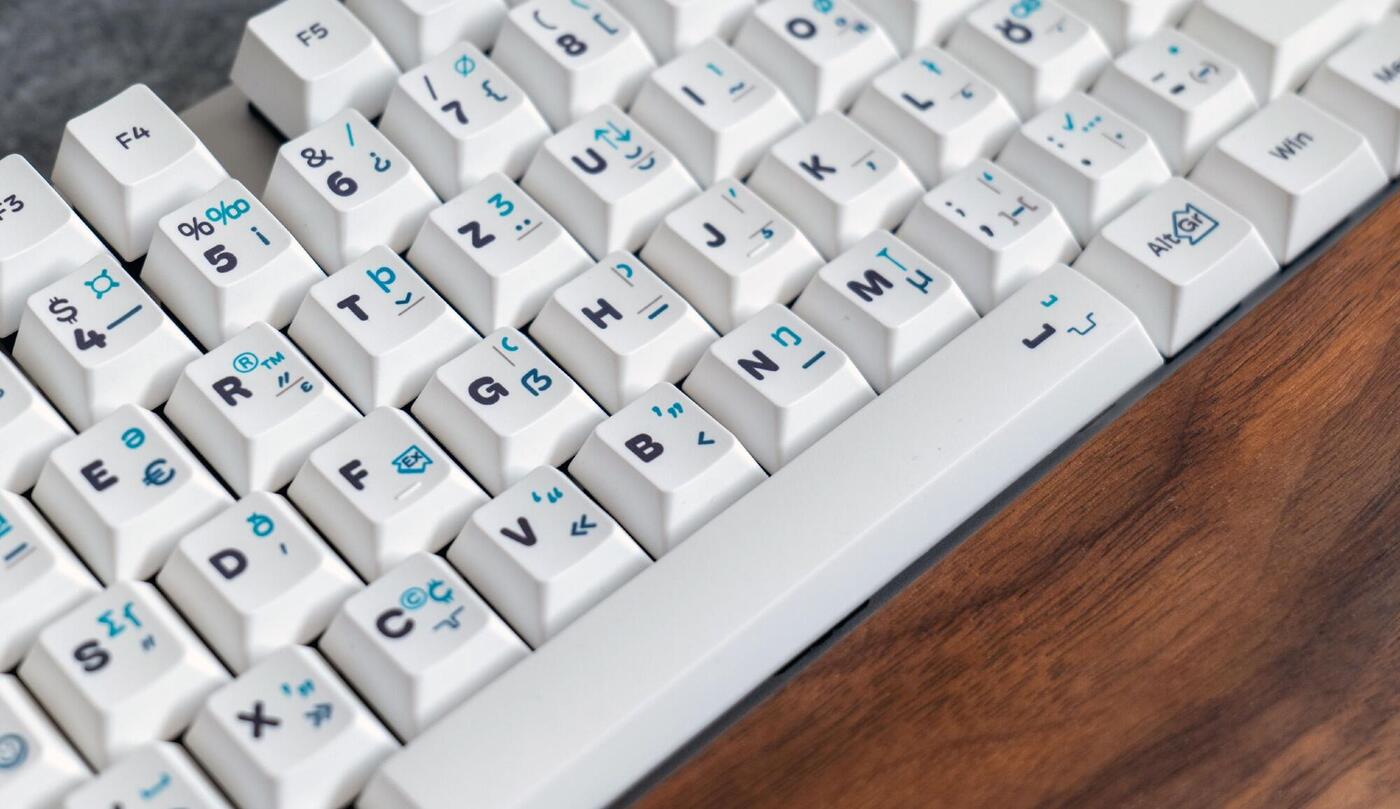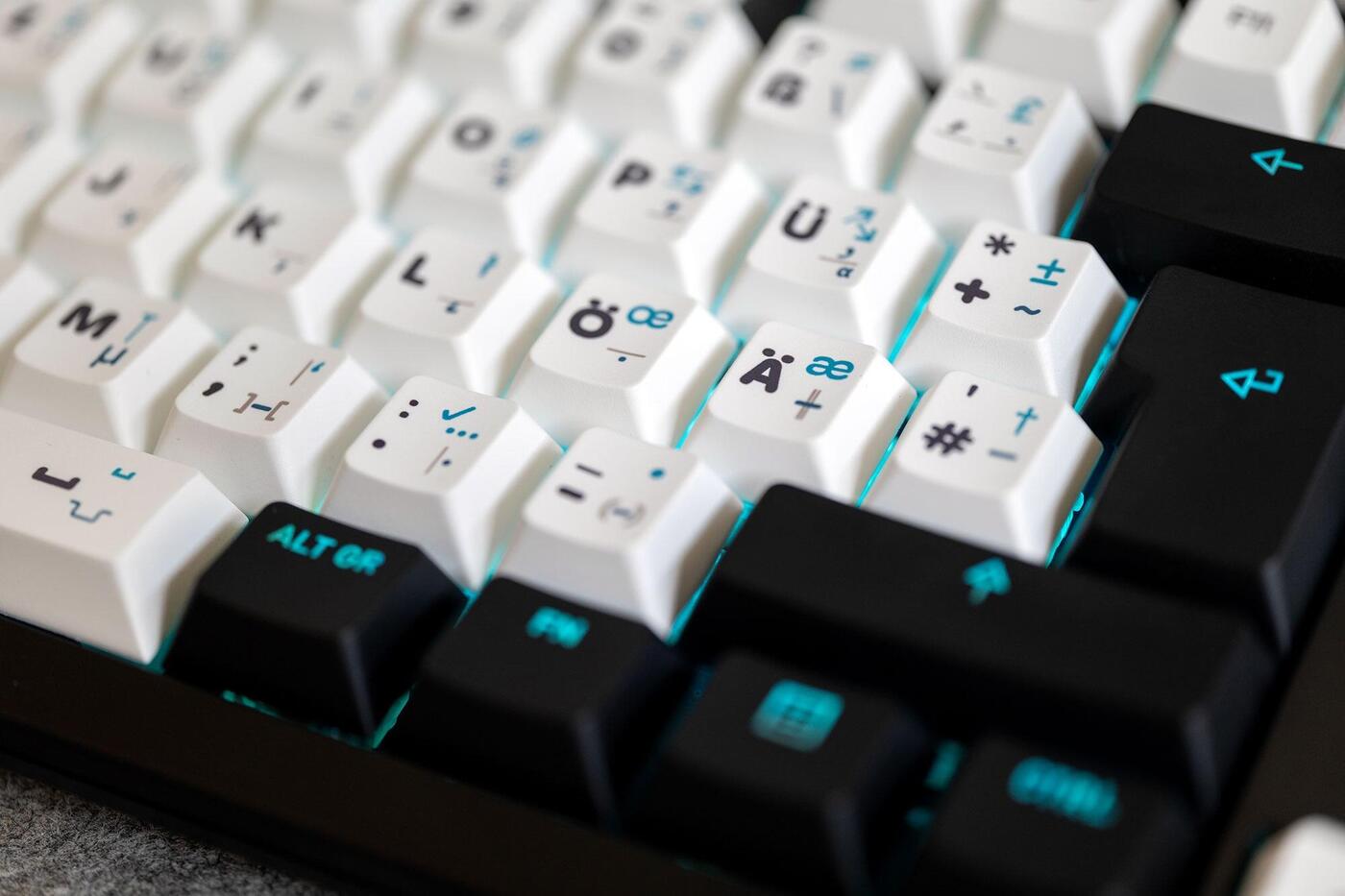
Die Lösung eines 150 Jahren alten Problems. Mit der Einführung der Schreibmaschine im 19. Jahrhundert wurde der ansonsten in der professionellen Drucksachenproduktion verfügbare Zeichensatz stark eingeschränkt. Es entstand die »Schreibmaschinen-Typografie«, bei der die typografisch korrekten Zeichen für zum Beispiel Apostroph, Anführungszeichen und Gedankenstrich nicht mehr auf Tastatur vorhanden sind und notdürftig ersetzt werden. Auch Computer-Tastaturen übernahmen später diesen beschränkten Zeichensatz. Wer auf einen größeren Zeichensatz zugreifen möchte, muss sich mit Notlösungen behelfen, da sämtliche massenproduzierte Tastaturen weiterhin auf dem einfachen Zeichensatz der Schreibmaschine beruhen. Bis jetzt!
Der komplette Zeichensatz professioneller Textverarbeitung kommt sichtbar auf die Tastatur.
Die TypoTasten sind ein Tastenkappenset für mechanische Tastaturen, das die erweiterte E1-Belegung nach DIN 2137 (2023) für Windows und MacOS nutz- und erstmals sichtbar macht. Die Idee dazu entstand innerhalb der Typografie.info-Community und wurde nun im Rahmen einer Kickstarter-Kampagne veröffentlicht.
Mit der E1-Belegung und unseren Tastenkappen kommen unter anderem diese Zeichen zusätzlich und sichtbar auf die Tastatur:
typografisch korrekter Apostroph (’)
typografisch korrekte Anführungszeichen (» « › ‹ „ “ ” ‘ ’)
Sekundenzeichen/Zollzeichen (″) und Minutenzeichen/Fußzeichen (′)
horizontale Striche: geschützter Bindestrich, Gedankenstrich, Geviertstrich, Minuszeichen
großes Eszett (ẞ) und langes s (ſ)
diaktritische Zeichen und Buchstaben von Amts- und Minderheitensprachen im lateinischen Schriftsystem
Leerräume (geschütztes Leerzeichen, schmales geschütztes Leerzeichen) und Bindehemmer für Ligaturen
verschiedene typografische Symbole (︎™︎, ︎®︎, ︎©, ¢, ⌀, ×, …, • etc.)
Außerdem macht die E1-Belegung folgendes ohne Tastenaufdruck erreichbar: Lautschriftzeichen des Internationalen Phonetischen Alphabets (IPA); mathematische und griechische Zeichen; Aufzählungs- und Schmuckzeichen; hochgestellte, tiefgestellte, eingekreiste Zeichen und vieles weitere mehr.
In diesen drei Schritten zur professionellen Typografie-Tastatur
Beispiel-Anwendung: Windows-TypoTasten auf Cherry G80-3000N RGB unter Beibehaltung der Original-Steuertasten.
Die Beschriftung der Tastatur erfolgt mehrfarbig im Thermosublimationsverfahren. Hierbei werden die Tasten unter Hitzeeinwirkung bis in die Tiefe eingefärbt. Es entsteht dabei eine langlebige Beschriftung, die auch bei jahrelanger Benutzung nicht abgerieben werden kann. Die mehrfarbige Ausführung erleichtert dabei die Orientierung und die Unterscheidung der Belegungsebenen sowie der druckenden Zeichen und nichtdruckenden Hilfszeichen (hellgrau).
Komfortable, systemübergreifende Bedienung und bessere Typografie
Das kurzfristige Ziel der Kampagne ist es, professionellen Anwendern die Möglichkeit einer Hardware-Umsetzung der E1-Tastatur zu geben und zeitgleich mehr Bewusstsein für die Existenz der erweiterten, normierten Tastaturbelegung zu schaffen.
Mit der DIN 2137 im Hintergrund hat die E1-Belegung das Zeug dazu, ein Standard in verschiedenen Berufs- und Anwendungsbereichen zu werden, wo eine typografisch korrekte Texteingabe von Belang ist. Denn die schlechte Erreichbarkeit der typografisch korrekten Zeichen führt regelmäßig zu einer mangelhaften oder gar falschen Anwendung von Satzzeichen und der schleichenden Etablierung der Schreibmaschinen-Typografie als Publikationsstandard. Mit der Etablierung von E1-Tastaturen kann dem mittelfristig entgegengewirkt werden.